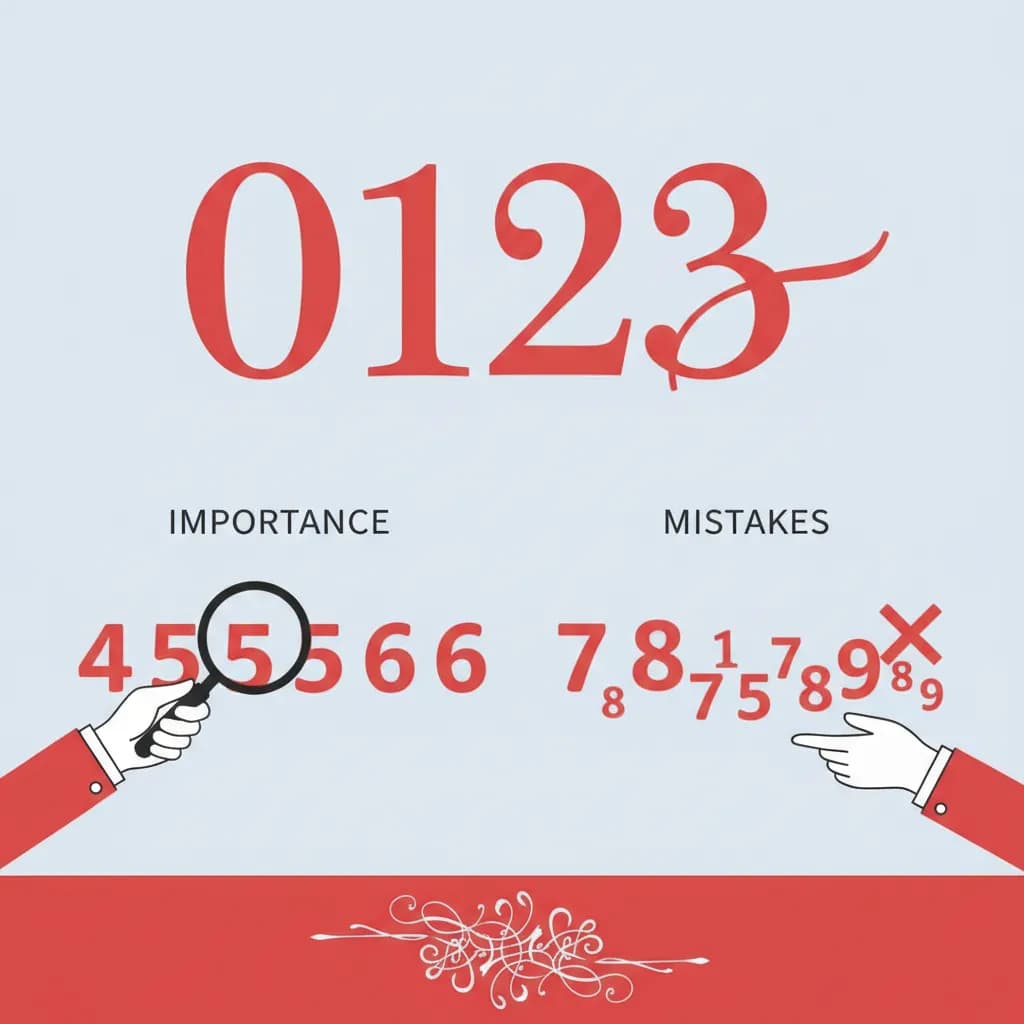
המעצבים מודאגים מאוד מהבחירה של הגופן לטקסט ולכותרות, אך לעיתים נדירות יותר הם מתמקדים בפונטים של מספרים. זו טעות יקרה. מספר שיוצג בגופן לא מתאים יכול לשבש את ההיררכיה החזותית של כל הדף, לבלבל את הקורא, ולהחליש את המסר של המותג. בין אם אתם מעצבים הזמנת חתונה, לוגו עסקי, כרזה לאירוע או ממשק דיגיטלי – פונטים של מספרים הם חלק בלתי נפרד מהשפה הטיפוגרפית שלכם. במדריך הזה נסביר מה הופך פונטים של מספרים למשפיעים, איך לבחור נכון לפי הצורך, ואיך להימנע מהטעויות שחוזרות שוב ושוב.
⚡ נקודות מפתח:פונטים של מספרים הם מערך הספרות שמעוצבות כחלק מגופן טיפוגרפי – ולכל גופן יש גרסת מספרים משלו, עם אופי ויזואלי ייחודי. בניגוד למה שחושבים רבים, לא כל גופן מייצר מספרים באותה איכות. ישנם גופנים שבהם המספרים מעוצבים בקפידה ומהווים חלק אינטגרלי מהשפה הטיפוגרפית, ואחרים שבהם המספרים נראים מוצמדים ולא שייכים.
בתחום ה-טיפוגרפיה הקלאסית קיימים שני סוגים עיקריים של פונטים של מספרים:
בנוסף, ישנה הבחנה חשובה בין Proportional Figures – מספרים עם רוחב משתנה לפי הספרה – לבין Tabular Figures – מספרים ברוחב אחיד, הכרחיים לטבלאות ודוחות כספיים. ב-Google Fonts ניתן לבדוק את תמיכת הגופן בסוגי מספרים שונים לפני שמורידים אותו.
לפי עקרונות ה-UX Research, בחירת פונטים של מספרים שאינה עקבית עם שאר הגופן עלולה לפגוע בקריאות ולהוסיף "רעש ויזואלי" שמפריע לתקשורת המסר. כאשר מעצבים בוחרים פונטים של מספרים בתשומת לב, הם יוצרים עיצוב שלם ומלוכד יותר.
הבחירה הנכונה של פונטים של מספרים תלויה ישירות בסוג הפרויקט ובמסר שרוצים להעביר. אין "פונט מספרים אוניברסלי" – כל הקשר עיצובי דורש גישה שונה.
להזמנות חתונה, שילוטים לאירועים ועיצובי "שמרו את התאריך", פונטים של מספרים צריכים להתאים לסגנון הקליגרפי של הטקסט. גופן כמו פונט ז׳ולייט, שהוא פונט קליגרפי עברי רומנטי, מדגים כיצד ניתן לשלב מספרים שמשתלבים בחלקה עם אותיות הסקריפט – ויוצרים הרמוניה ויזואלית מלאה.
למיתוג עסקי, פונטים של מספרים צריכים לשדר מקצועיות ואמינות. גופנים מסוג Sans-Serif עם Tabular Figures מתאימים לדוחות, מחירונים וממשקים דיגיטליים. לעומת זאת, לוגו שמכיל מספר (שנת ייסוד, ספרה מזהה) דורש פונט מספרים שמתאים לאופי הגרפי הכולל. כדאי לבחון את עקרונות עיצוב גופן עברי כדי להבין כיצד אופי הגופן משפיע על תפיסת המותג.
בממשקים דיגיטליים, פונטים של מספרים חייבים להיות קריאים גם בגדלים קטנים. Tabular Figures הם כמעט חובה כאשר מציגים נתונים בטבלאות, שעונים, מחשבונים או לוחות מחירים. גופן כמו פונט דיפלומט – שמציע מגוון משקלים ותמיכה בטקסט רץ – הוא דוגמה לגופן שבו פונטים של מספרים מעוצבים לתמוך גם בתצוגה דיגיטלית.
מניסיון עם מגוון פרויקטים עיצוביים, ישנם כמה כללי אצבע שחוסכים הרבה תיקונים מיותרים בשלב הגמר:
שלב 1: הגדירו את ההקשר
האם המספרים מופיעים בטקסט רץ, בכותרת, בטבלה, או כאלמנט עיצובי עצמאי? ההקשר קובע את סוג פונטים של מספרים הנדרש.
שלב 2: בחרו את סוג הגופן
Lining לכותרות ותצוגת נתונים, Old-Style לטקסט ספרותי ואלגנטי, Tabular לטבלאות ומחשבונים.
שלב 3: בדקו התאמה לשאר הגופן
הציגו את המספרים לצד האותיות בפרויקט. שימו לב לגובה, לעובי הקו ולאופי הכללי – האם הם משתלבים?
שלב 4: בחנו בתנאים אמיתיים
ייצאו פרופ, הציגו על מסך ועל הדפסה. פונטים של מספרים שנראים טוב בתצוגת עריכה עשויים להיראות שונה לחלוטין בפרויקט הסופי.
⚡ נקודת מפתח:
גם מעצבים מנוסים נופלים בפחים הבאים כשמדובר בפונטים של מספרים. הנה הטעויות הנפוצות ביותר – ואיך לתקן אותן:
פונטים של מספרים בסגנון Lining בתוך פסקת טקסט ארוכה יוצרים "רעש ויזואלי" – הספרות בולטות יתר על המידה ביחס לאותיות. הפתרון הוא להשתמש ב-Old-Style Figures בטקסט רץ, ולשמור את Lining לכותרות ונתונים.
כשמשתמשים בשני גופנים שונים לטקסט ולמספרים – ללא תכנון מוקדם – התוצאה נראית לא מלוכדת. פונטים של מספרים חייבים להיות חלק מהשפה הטיפוגרפית הכוללת. בחרו גופן שמכיל מספרים מעוצבים כחלק אינטגרלי ממנו.
גופנים קליגרפיים לעתים קרובות מכילים מספרים שלא תואמים לאופי האותיות. מעצבים רבים לא בודקים זאת ומגלים את הבעיה רק בשלב ההדפסה. לפני בחירת גופן קליגרפי לפרויקט שכולל תאריכים או מספרים, בדקו את פונטים של מספרים שלו ספציפית. תוכלו ללמוד עוד על גופנים כתב יד שמוסיפים אישיות לעיצוב ולבחון כיצד הם מטפלים במספרים.
כשפונטים של מספרים הם Proportional, עמודות של מחירים או נתונים נראות מבולגנות – כל שורה "מוזזת" ויזואלית. זו אחת הטעויות הכי נפוצות בעיצוב ממשקים. ה-Google Fonts מאפשר לסנן גופנים לפי תמיכה ב-Tabular Figures – כלי שכדאי להכיר לפני כל פרויקט עם נתונים.
סוג פונטים של מספרים מתאים ל לא מתאים ל Lining Figures כותרות, לוגואים, נתונים טקסט רץ ארוך Old-Style Figures טקסט ספרותי, עיצוב קלאסי טבלאות, ממשקים דיגיטליים Tabular Figures טבלאות, מחירונים, דוחות עיצוב קליגרפי, כותרות אלגנטיות Proportional Figures כותרות, עיצוב חופשי עמודות מספרים, חישוביםLining Figures הם מספרים שכולם באותו גובה, מיושרים לשורת הבסיס – מתאימים לכותרות ונתונים. Old-Style Figures הם מספרים עם עליות וירידות שונות, הדומים לאותיות כתב יד – מתאימים לטקסט רץ ולעיצובים קלאסיים. הבחירה ביניהם תלויה בהקשר העיצובי ובאופי הפרויקט.
לא תמיד. בגופנים עבריים, המספרים הם מערביים (לטיניים) ועוצבו בנפרד מהאותיות. חשוב לבדוק את ההתאמה הויזואלית – גובה, עובי קו ואופי – בין פונטים של מספרים לאותיות הגופן העברי לפני הבחירה הסופית. גופנים מקצועיים כמו אלה של Lia Fonts מקפידים על עקביות בין האותיות למספרים.
Tabular Figures נחוצים בכל מקום שבו מספרים מופיעים בעמודות – טבלאות, מחירונים, דוחות כספיים, לוחות זמנים. הם מבטיחים שכל ספרה תופסת רוחב זהה, כך שהעמודות נראות מיושרות ומסודרות. ללא Tabular Figures, עמודות מספרים נראות "זיגזג" ויזואלי שפוגע בקריאות.
כשבוחרים פונטים של מספרים בתשומת לב – בהתאם להקשר, לסוג הפרויקט ולאופי הגופן הכולל – הפרויקט מרוויח עקביות ויזואלית שמורגשת גם אם הצופה לא מצליח לנסח מדוע. ניתן ללמוד עוד על מבנה הגופן העברי כדי להעמיק את ההבנה הטיפוגרפית, ולהתייעץ עם Google Fonts לבחינת גופנים שתומכים בסוגי מספרים מגוונים.